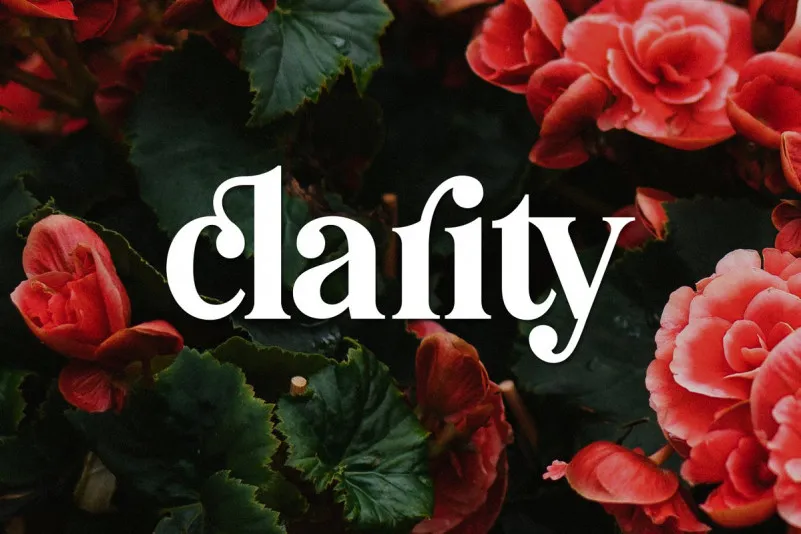
Agradecemos pela consulta à Pioggia Modern Serif Font! Essa tipografia serifada moderna e divertida é uma criação do Twicolabs Fontdation, desenvolvida com um toque de amor para as pequenas detalhes que marcam o estilo. Pioggia é a versão mais clara e minimalista da família, perfeita tanto para usar em projetos profissionais quanto para aqueles que querem trazer um pouco de criatividade às suas criações. Seja você designer, publicitário ou simplesmente alguém que ama uma boa fonte, Pioggia Modern Serif é o tipo certo para tornar seu trabalho ainda mais atraente e único. Este é mais do que apenas uma fonte: ele é uma arte em constante evolução.